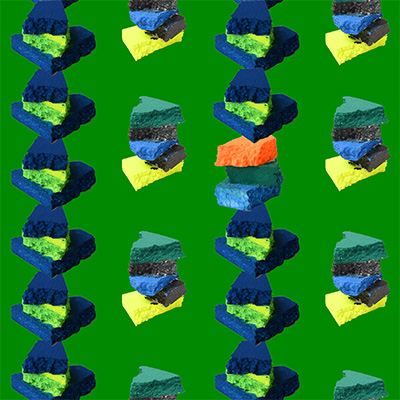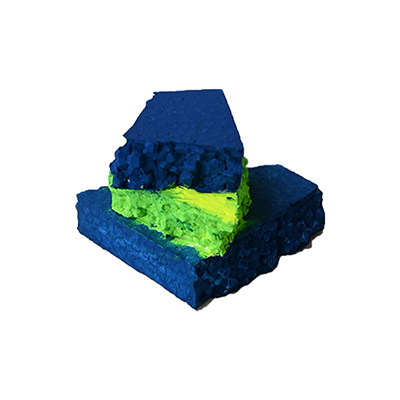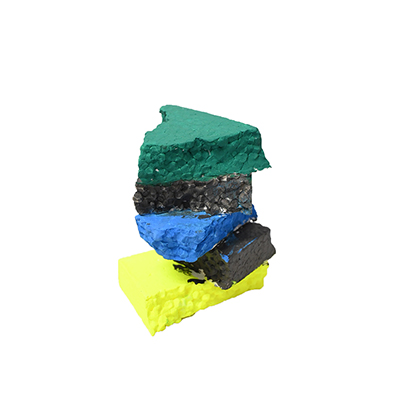
満彩
色彩のリズム、心躍る満彩
Artist地代所 愛
Designerジャンウェイ
Organizationワークささはた
楽しかったです。(地代所 愛)
地代さんが制作した作品です。細部まで丁寧に塗り重ね、全体を鮮やかな色彩で満たしました。その豊かないろづかいから、地代さんの明るく前向きな人柄がよく伝わってきます。(ジャンウェイ)
アーティストの丁寧な塗り方が本人をよく表しています。(ワークささはた)